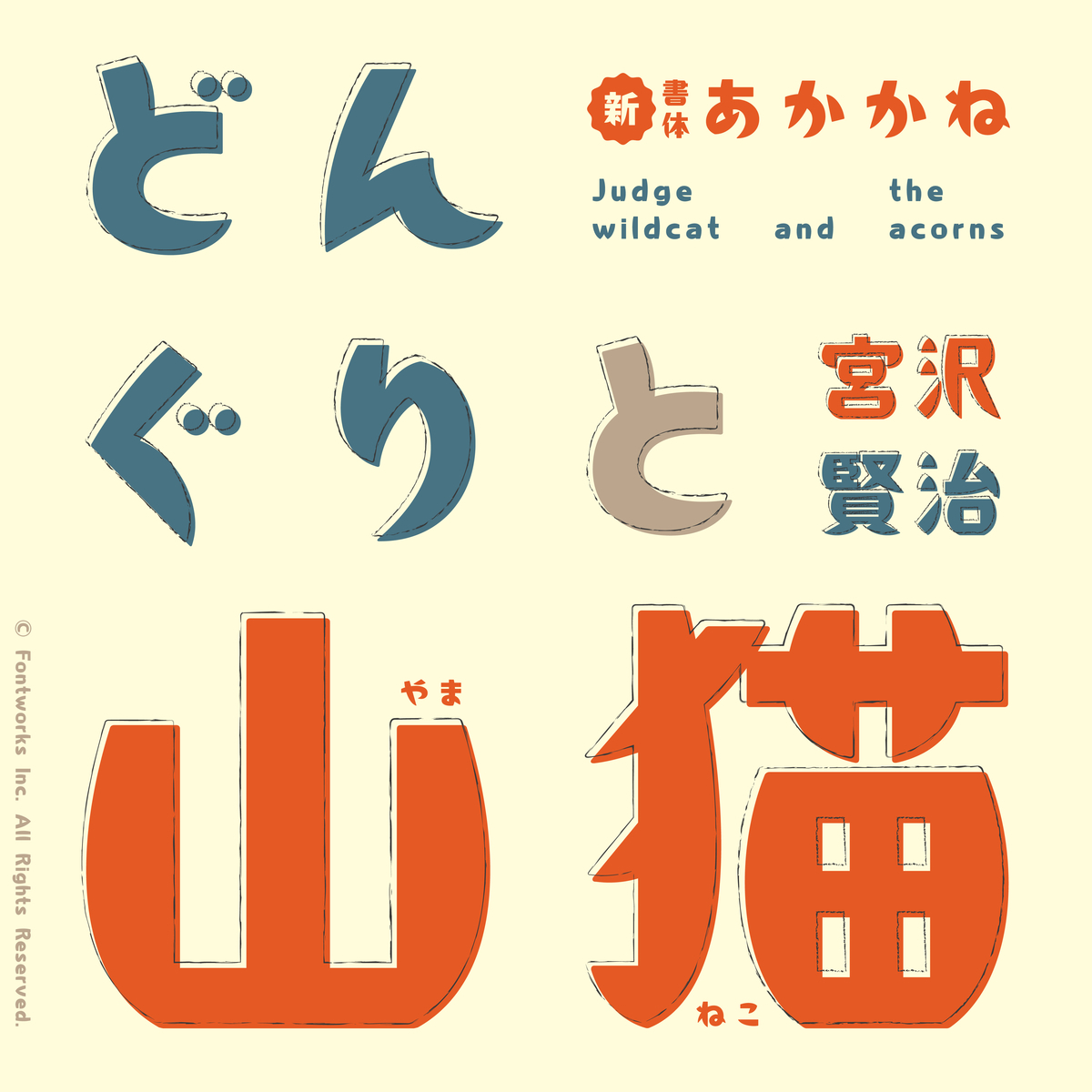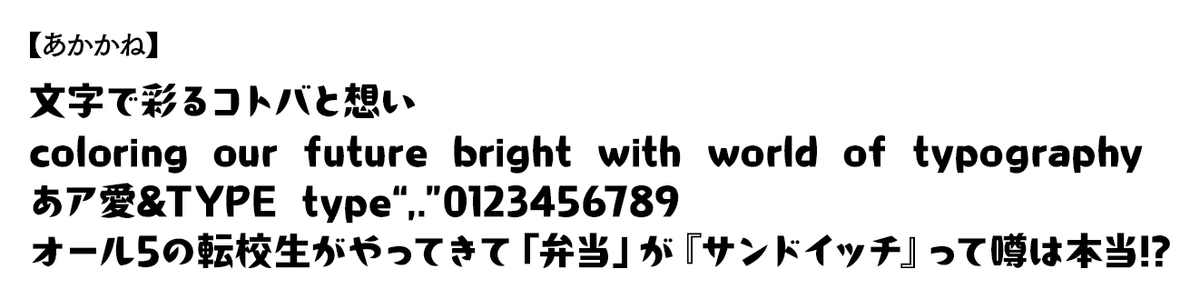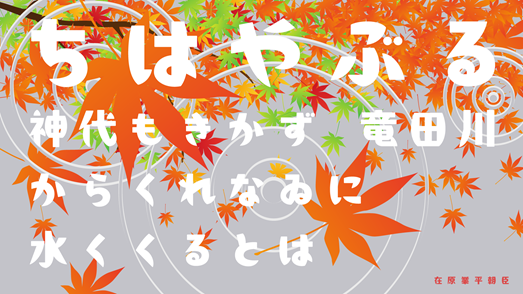
フォントワークスが新書体「あかかね」を目と耳で感じるスペシャルサイト公開
フォントワークスは、2022年9月にリリースした新書体「あかかね」を目と耳で感じるスペシャルサイトを公開した。
フォントワークス新書体「あかかね」
書体デザイナー・大崎善治氏による新書体「あかかね」は、縦画と外側の丸みが特長の書体で、主張がありながらどこか素朴でかわいらしい印象を持つ。特に漢字は同じ部品でも字によって少しずつ印象が異なり、それぞれのキャラクター性がユニーク。視認性とデザイン性を併せ持つので、様々な場面で使用できる。
目と耳で感じる「あかかね」スペシャルサイト
「あかかね」の魅力を知ることができるスペシャルサイトがオープン。
新進気鋭のクリエイターである東條あずさ氏を起用し、「あかかね」のイメージムービーを制作。
太めの線でデザイン性と視認性が両立している点や、あえて細部を統一せず有機的な雰囲気を残すことで、賑やかな街中の看板などで広く使われる様子を表現している。
目と耳で「あかかね」の世界観を感じてみよう。
「あかかね」書体デザイナー 大崎善治Profile